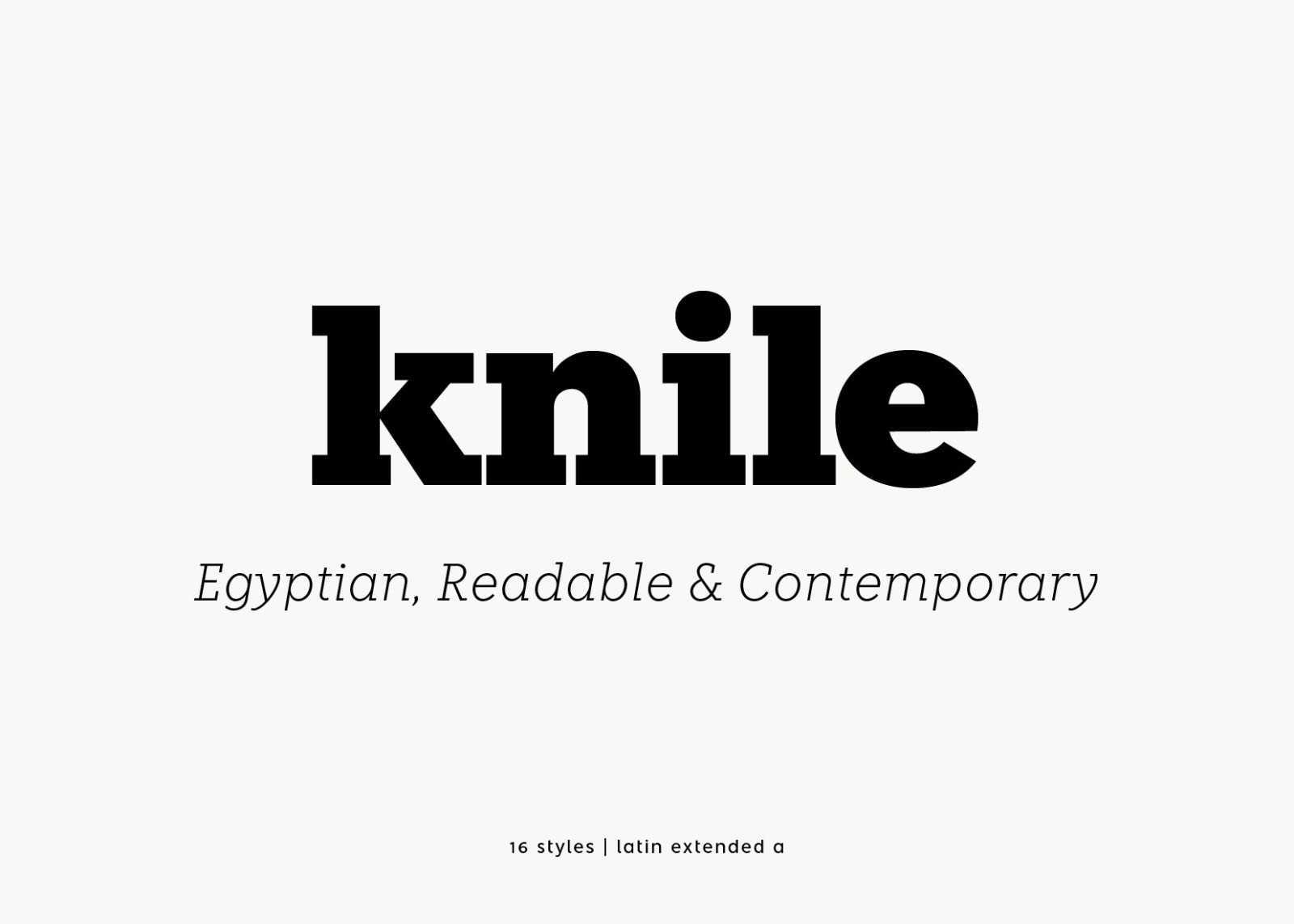
Knile é uma fonte slab serif que oferece uma ampla gama de 8 pesos diferentes, cada um acompanhado de uma versão em itálico. Isso resulta em uma total de 16 estilos de fontes distintos. Com seu design altamente legível, a fonte é perfeita tanto para headlines quanto para o texto de corpo, tornando-a uma escolha ideal para qualquer tipo de projeto gráfico. Você pode agora experimentar o recurso de fonte Knile Slab Serif em sua versão de teste, que inclui as fontes normais e itálicas. Explore as diferentes opções de Knile e descubra por que esta fonte é uma opção confiável para seus projetos.